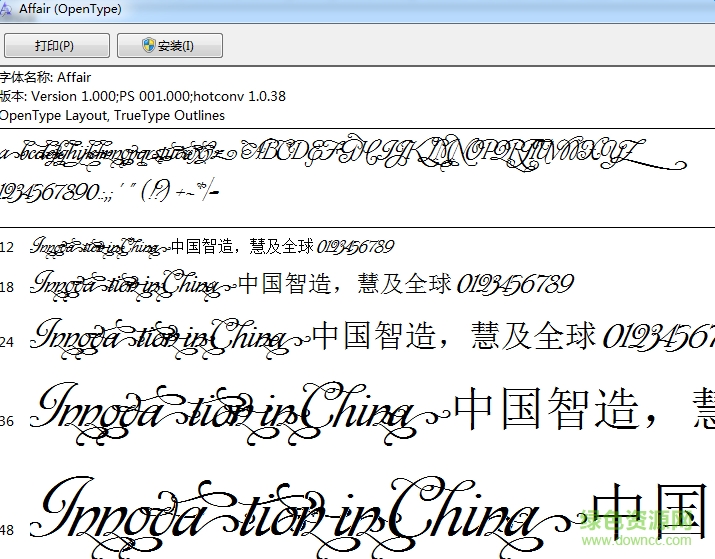
affair字體是一款英文字體庫(kù)中的個(gè)性字體,該字體可廣泛應(yīng)用于平面設(shè)計(jì)、廣告設(shè)計(jì)、報(bào)紙雜志、正文標(biāo)題等領(lǐng)域,喜歡的網(wǎng)友可免費(fèi)下載收藏。
affair字體是一款極具個(gè)性的英文字體,該字體非常飄逸,但是整體卻又不失個(gè)性。有喜歡的朋友趕快來(lái)綠色資源網(wǎng)下載使用吧!